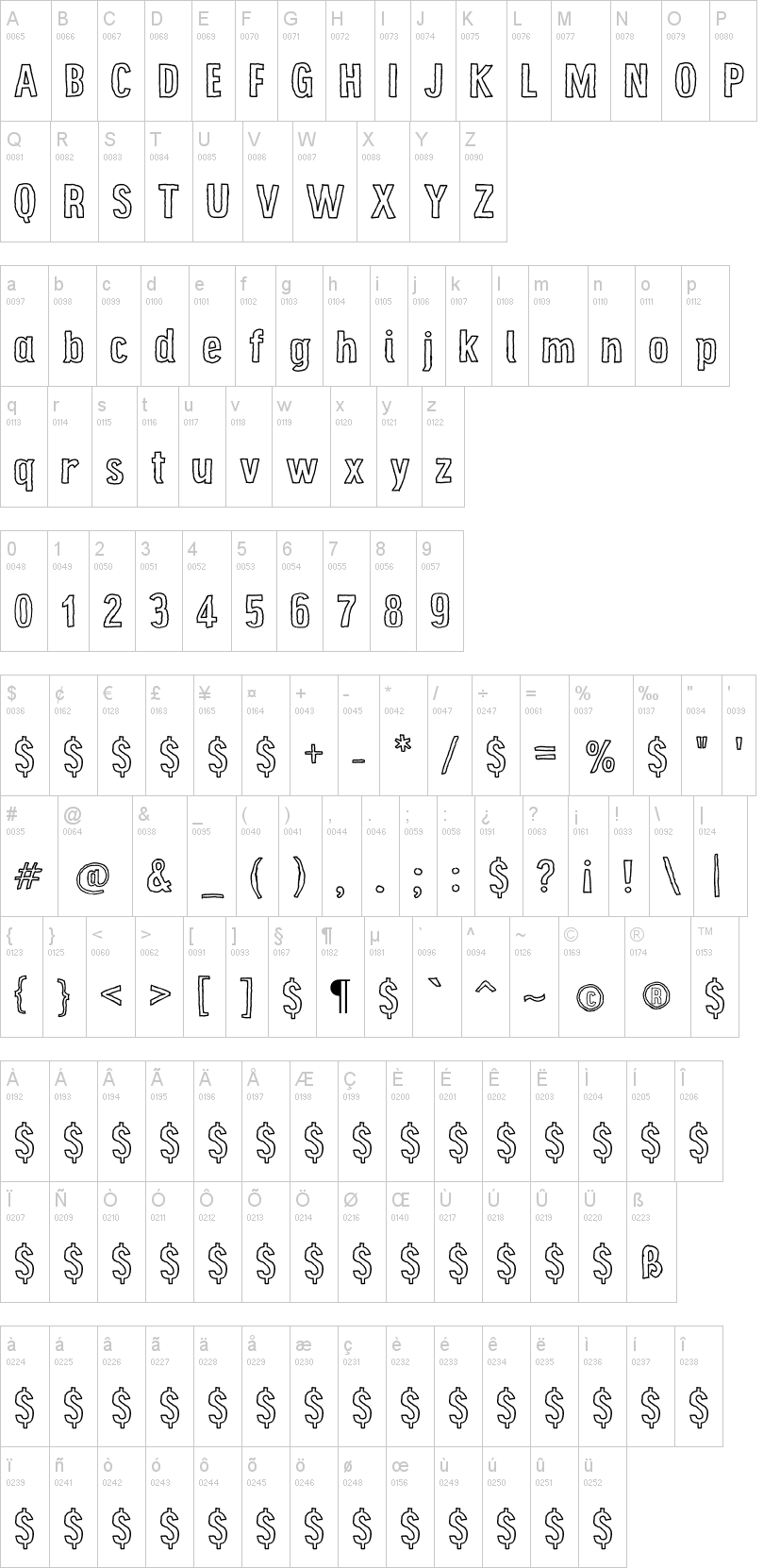
Grunge Poster 字体是一款复古风格的字体,它具有模糊、不规则、粗糙和非常破旧的外观,通常用于设计海报、T恤、标识等。Grunge Poster 字体的特点是它的字母和字符都具有模糊的边缘,这使得字体看起来更加有趣。它的文字也有一定的倾斜,使得它看起来更加有力。Grunge Poster 字体的另一个特点是它有一个大胆的外观,它能够抓住人们的眼球,吸引人们的注意力,从而使您的设计更加出彩。内容介绍
Grunge Poster是一款非常不错的手写艺术字体,具有很好的视觉感,适合于文化类的宣传设计、商业类品牌的广告和产品包装设计以及个性化文字排版等较多场景。